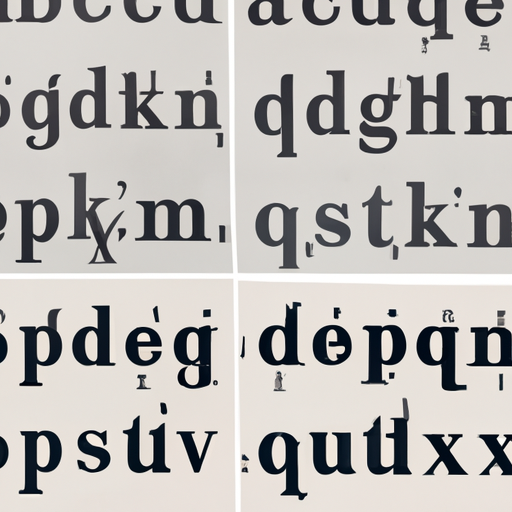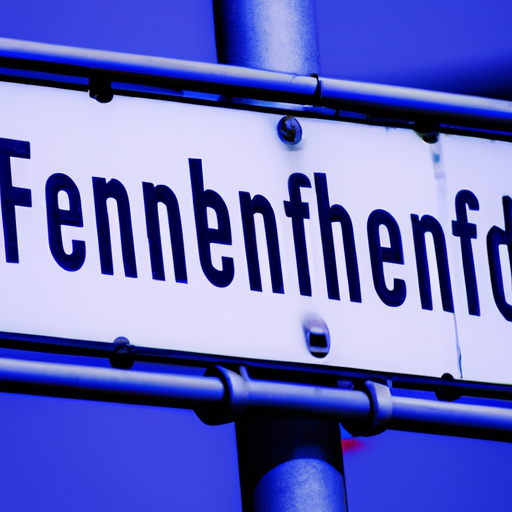
10 גופנים הכי נפוצים שיש
בעולם העצום של הטיפוגרפיה, גופנים שונים מחזיקים במקומות שלהם עם מאפיינים ושימוש ייחודיים. פוסט זה בבלוג שופך אור על 10 הגופנים הנפוצים ביותר שנמצאים בשימוש נרחב בתחומים שונים, החל מסמלים ואתרי אינטרנט ועד ספרים ומסמכים רשמיים. גלה את ההיסטוריה, המאפיינים שלהם ומדוע הם כל כך פופולריים.
1. 'Times New Roman': סוס העבודה הטיפוגרפי המוגדר כברירת מחדל?
Times New Roman הוא ללא ספק אחד הגופנים המוכרים ביותר בעולם. פותח על ידי סטנלי מוריסון וויקטור לרדנט בשנת 1932, הוא הפך לגופן ברירת המחדל עבור מסמכים ופרסומים רבים. העיצוב הקלאסי והאלגנטי שלו מקל על הקריאה בפורמט מודפס ודיגיטלי. ניתן לייחס את הפופולריות של הגופן לזמינותו הנרחבת ולתאימותו למערכות הפעלה ותוכנות שונות.
אחת הסיבות לכך שהטיימס ניו רומן נשאר בחירה פופולרית היא הרבגוניות שלו. הוא נפוץ בעבודות אקדמיות, מסמכים מקצועיים והתכתבויות עסקיות. המשיכה הנצחית שלו הופכת אותו למתאים למגוון רחב של יישומים. בנוסף, הסגנון הסריף שלו, עם קווים קטנים בקצות התווים, משפר את הקריאות והקריאה, במיוחד בחומרים מודפסים.
עם זאת, ישנם ויכוחים לגבי ההתאמה של Times New Roman בהקשרים מסוימים. יש הטוענים שהשימוש הנרחב בו הפך אותו לקלישאה ולבחירה בטוחה, חסרת יצירתיות ומקוריות. אחרים מאמינים כי נוכחותו בכל מקום הפכה אותו לפחות ייחודי ובלתי נשכח. עם זאת, ההיכרות והקריאה שלו ממשיכות להפוך אותו לחביב מתמשך בקרב סופרים, עורכים ומעצבים רבים.
1. תמונה המתארת טקסט לדוגמה בגופן Times New Roman.
2. 'Arial': פונט מודרני ללא סריף לעידן דיגיטלי
בעידן הדיגיטלי, אריאל התגלתה כבחירה פופולרית הן לתוכן מקוון והן לא מקוון. פותח על ידי Monotype Imaging בשנת 1982, Arial הוא גופן sans serif הידוע במראה הנקי והמודרני שלו. הפשטות והרבגוניות שלו הופכות אותו למתאים למגוון רחב של יישומים, מאתרי אינטרנט ופרסומות ועד למצגות ושילוט.
אחד היתרונות המרכזיים של Arial הוא הקריאות שלה, במיוחד בפורמטים דיגיטליים. הקווים הנקיים ומרווח האותיות האחיד שלו מקלים על הקריאה במסכים בכל הגדלים. בין אם זה על צג מחשב, סמארטפון או טאבלט, Arial מבטיחה שהטקסט יישאר ברור וקריא, גם בגדלים קטנים.
יתרה מכך, הזמינות הנרחבת של Arial על פני מערכות הפעלה ופלטפורמות תוכנה שונות תרמה לפופולריות שלה. זהו גופן ברירת מחדל ביישומים רבים, מה שהופך אותו לנגיש למספר רב של משתמשים ברחבי העולם. זה מבטיח עקביות ותאימות בין מכשירים ופלטפורמות שונות, דבר חיוני בנוף הדיגיטלי המחובר הדדית של ימינו.
עם זאת, ישנם מבקרים הטוענים כי אריאל חסר מקוריות ואופי. יש הטוענים כי נעשה בו שימוש יתר והפך לשם נרדף לעיצוב גנרי וחסר השראה. עם זאת, לא ניתן להכחיש את הפופולריות והפונקציונליות של Arial. האסתטיקה הנקייה והמודרנית שלו, בשילוב עם קריאותו בפורמטים דיגיטליים, הופכים אותו לבחירה מצוינת להעברת מידע בצורה יעילה בעידן הדיגיטלי שלנו.
3. "'Helvetica': מדוע זה נחשב לגופן המושלם?
Helvetica, גופן נצחי ואייקוני, נחשב לאחד הגופנים המושלמים ביותר שנוצרו אי פעם. העיצוב הפשוט והנקי שלו הפך אותו למרכיב בסיסי בעיצוב גרפי, מיתוג ופרסום כבר למעלה מחצי מאה. Helvetica, שפותחה בשנת 1957 על ידי מעצב הגופן השוויצרי מקס מידינגר, צברה פופולריות במהירות בשל הרבגוניות והקריאות שלה.
אחת הסיבות מדוע Helvetica נתפסת כגופן המושלם היא הנייטרליות שלו. הפרופורציות המאוזנות והמראה הנייטרלי שלו מאפשרים לו להשתלב בצורה חלקה בכל עיצוב או הקשר מבלי להכריע את המסר. בין אם הוא משמש עבור לוגו ארגוני, שילוט או טקסט גוף, האופי הבלתי פולשני של Helvetica מבטיח שהפוקוס יישאר בתוכן.
הקריאות של Helvetica היא גורם נוסף שתורם לשלמות שלה. צורות האותיות הברורות והמוגדרות היטב מקלות על הקריאה בגדלים שונים ובאמצעים שונים. מאותיות קטנות על אריזות ועד שילוט בקנה מידה גדול, Helvetica שומרת על הקריאות והבהירות שלה, ומבטיחה שהמסר מועבר בצורה יעילה.
השימוש וההכרה הנרחבת של Helvetica ממלאים גם תפקיד משמעותי במוניטין שלה כגופן המושלם. זה הפך לגופן אוניברסלי, שאומץ על ידי אינספור מותגים, מוסדות ופרסומים ברחבי העולם. נוכחותו בכל מקום יצרה תחושה של היכרות ואמון עבור הקהל, מה שהופך אותו לבחירה אמינה עבור מעצבים המבקשים לבסס תחושה של מקצועיות ואמינות.
יתר על כן, הרבגוניות של Helvetica מאפשרת לה להתעלות מעבר לזמן ולטרנדים. זה הוכיח את אורך חייו בכך שהוא נשאר רלוונטי ושימוש נרחב בתקופות שונות ובתנועות עיצוב שונות. המשיכה הנצחית שלו נובעת מהיכולת שלה להסתגל ולהישאר נעימה ויזואלית, ללא קשר להעדפות עיצוב משתנות.
3. תמונה המציגה שלט רחוב בגופן Helvetica בסביבה מטרופולינית.
4. 'שליח חדש': האם זה עדיין הגופן המועדף לתסריטים?
כשמדובר בכתיבת תסריטים, בחירת הגופן היא קריטית לעיצוב ולקריאה. במשך שנים רבות, 'Courier New' הוא הגופן הרצוי לתסריטאים בשל מאפייניו הייחודיים. עם זאת, עם הופעת תוכנת כתיבת תסריט דיגיטלית והתפתחות תקני התסריטאות, ההעדפה של 'שליח חדש' מאותגרת.
• 1. הערעור המסורתי:
אחת הסיבות העיקריות לכך ש'Courier New' הפך לגופן המועדף לתסריטים היא המראה המסורתי דמוי מכונת הכתיבה שלו. הדמויות ברוחב הקבוע של 'שליח חדש' מעניקות לתסריט תחושה נבדלת ורטרו, המזכירה את הימים שבהם התסריטים הוקלדו על מכונות כתיבה של ממש. הפנייה הנוסטלגית הזו הפכה אותה לבחירה מוכרת בקרב תסריטאים ואנשי מקצוע בתעשייה.
• 2. המעבר לדיגיטל:
עם עליית תוכנות כתיבת תסריט דיגיטליות, כמו Final Draft ו-Celtx, פחתה ההסתמכות על 'Courier New'. תוכנות אלו מציעות מגוון אפשרויות גופנים, המאפשרות לכותבים לבחור גופנים המתאימים להעדפותיהם האישיות ולשפר את הקריאה. יתר על כן, תוכניות אלו פורמטים אוטומטית את הסקריפט בהתאם לסטנדרטים בתעשייה, ומבטלים את הצורך בבחירת גופן ספציפית.
• 3. קריאה ונגישות:
אמנם 'Courier New' זכה לשבחים על הקריאה שלו על הנייר, אך ייתכן שהוא לא יתרגם היטב במסכים דיגיטליים. יש הטוענים שגופנים אחרים, במיוחד סאנס-סריף כמו 'Arial' או 'Helvetica', מציעים קריאות טובה יותר במסכים, במיוחד במכשירים קטנים יותר כמו מחשבים ניידים או טאבלטים. תסריטאים צריכים לשקול את המדיום דרכו יקראו התסריטים שלהם ולהבטיח שהגופן הנבחר שומר על קריאה מיטבית.
10 הגופנים הנפוצים ביותר:
גופן נוהג מקור מחיר (ILS)
Helvetica לוגו ואתרי אינטרנט שוויץ, 1957 150₪
אריאל ספרים ומסמכים רשמיים צרפת, 1982 250₪
Times New Roman עיתונים בריטניה, 1931 350₪
גארמונד כתבי עת צרפת, 1530 400₪
גופנים הם יותר מסתם בחירות אסתטיות. הם כלים הנושאים את הטון, המסר והמותג של התוכן שלך. הבנת הגופנים הנפוצים ביותר והיישומים שלהם יכולה לשפר מאוד את התקשורת שלך בפורמטים מודפסים ודיגיטליים כאחד. בין אם אתה מעצב, סופר או בעל עסק, בקיאות בגופנים הללו יכולה לשפר את היכולת שלך למשוך את הקהל שלך.
עוד באותו הנושא:
פונט אברהם
פונטים לאנימציה: טיפוגרפיה דינמית בעידן הדיגיטלי